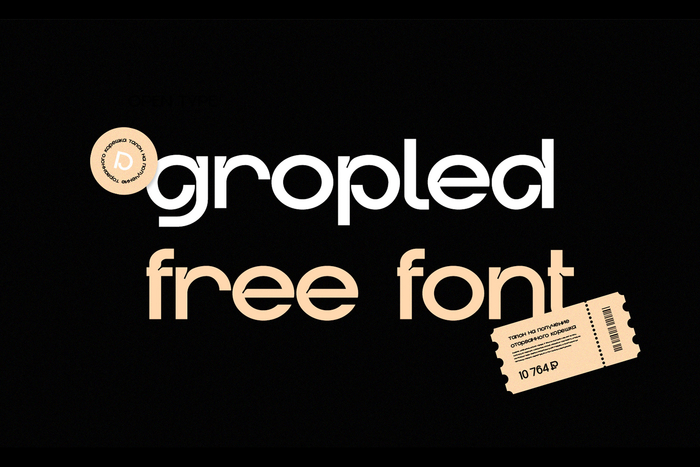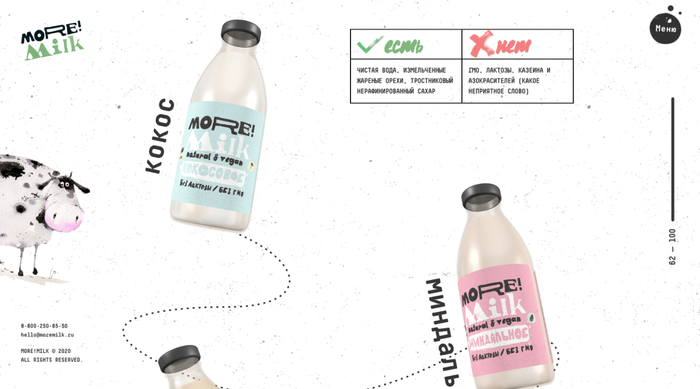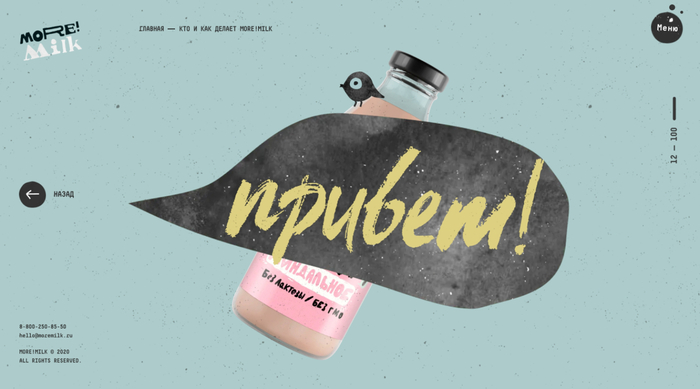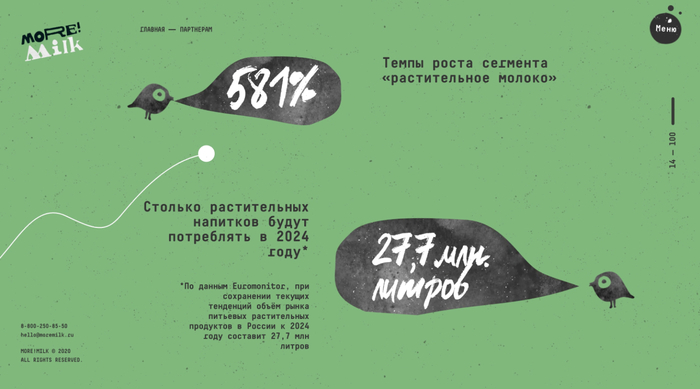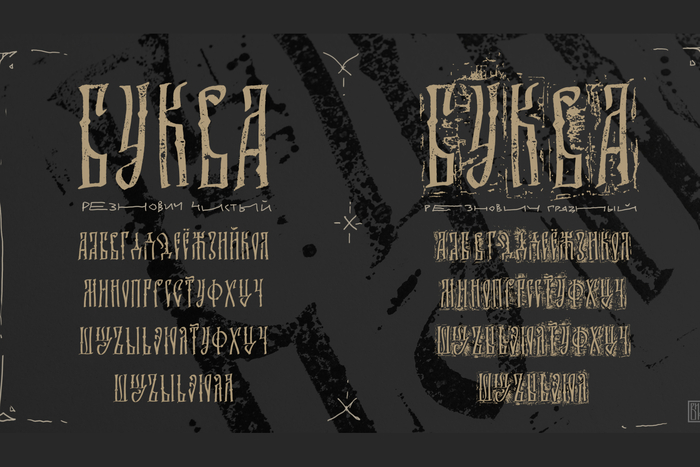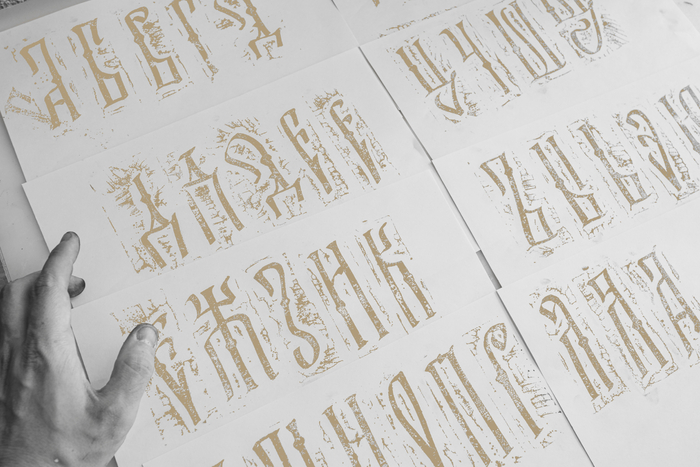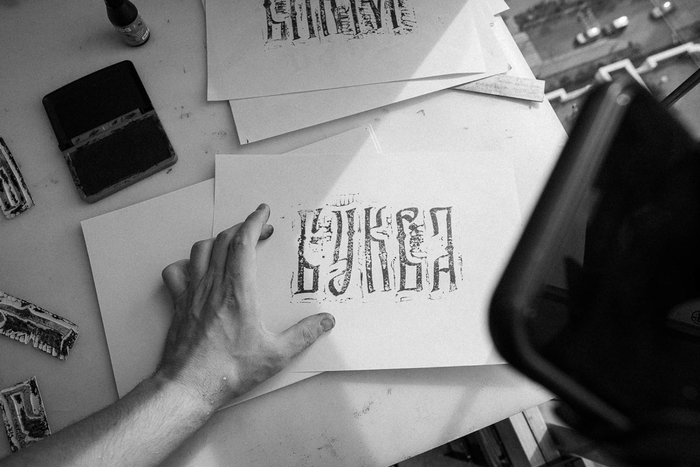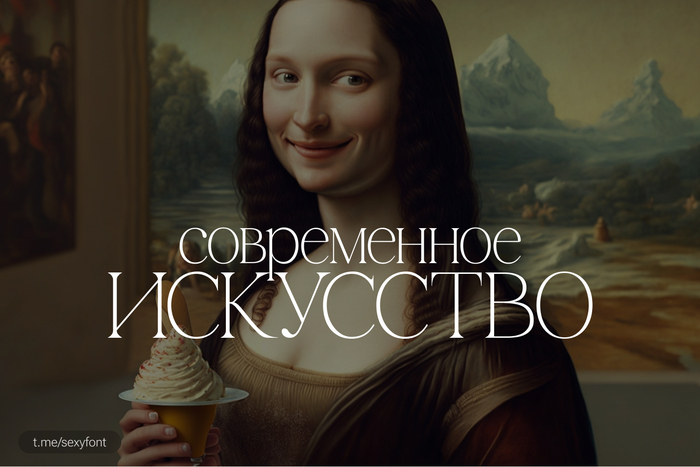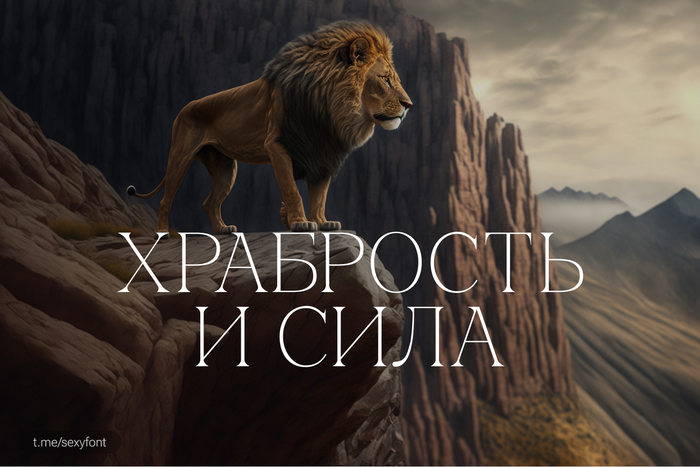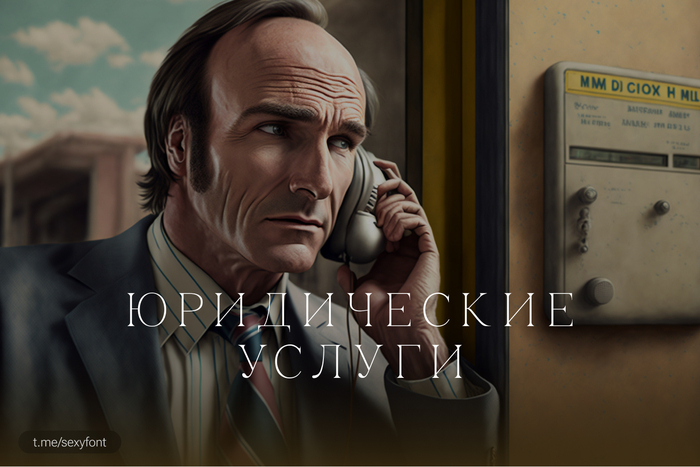
Кириллические шрифты
Шрифты на сайте. Новая рубрика
Суть: беру сайт с кириллическим шрифтом и по красоте показываю, что там за шрифты. А иногда даже ссылочкой поделюсь. Сегодня сайт с молочком. С обалденной анимацией и графикой.
Сайт: moremilk.ru. Автор: Кирилл Ким.
Шрифты:
– Iriska_Free (тот, что рисованный, почеркушки) Бесплатно для коммерческого использования.
– decimamonopro (основной гротеск) Бесплатно для личного использования
Кириллический шрифт в восточном стиле
Шрифт имеет два начертания: обычный и курсив. Все остальное ты увидишь в моей презентации. Хорошие, читаемые почеркушки. Моего стереотипного мышления об Азии хватило на: суши, Брюса, авто и анимэ. Сорян)
Шрифт: Belepotan. Автор: Locomotype. Презентация: моя.
Reznovich. Необычный нарезной шрифт для коротких заголовков
Reznovich
Необычный нарезной шрифт для коротких заголовков.
От автора: «полностью бесплатный шрифт для пользования и экспериментов. В прошлом году вырезал буквы для мастер-класса с детьми, пролежали год без дела — собрал их воедино и делюсь.»
Автор: Viktor Pushkarev
Шрифт Felidae
Красивая антиква. Отличный шрифт с засечками, сочетающий в себе итальянское возрождение и современность.
Автор: Dariya Kazakova
Презентация: Моя, сделал через нейросети.
Чебурнатор. С помощью нейросетей и немного фантазии
Нейросети. ЯтвойШрифт.
Шрифты всегда были больше про шутки и мемы, нежели сами шрифты. Теперь я хочу представить вам новую рубрику. А возможно и уровень. Теперь это еще и истории.
Знакомься. Шрифты из фильмов. Чебурашка в параллельной вселенной.
Презентация: Амир Исламов
Автор кириллизации: Евгения Тишина
Кириллический шрифт Gropled
Бесплатная, читаемая кириллица. Действительно хороший шрифт с необычными буквами)
Автор: Daniyar Shape. Презентация от автора шрифта
Какой-то старославянский шрифтец
Классный старославянский шрифт для твоих проектов.
Пару таких шрифтов определенно должны лежать в твоей библиотеке)
Шрифт Balkara.
Шрифт Tablon. Кириллица
Привет пикабу! Спортивный шрифт Таблон Таблонович зовет тебя на зарядку. Пора размять свои затверденелые булки. Прям сейчас сделай 3 приседания или отжимания.
Автор: Cristian Tournier